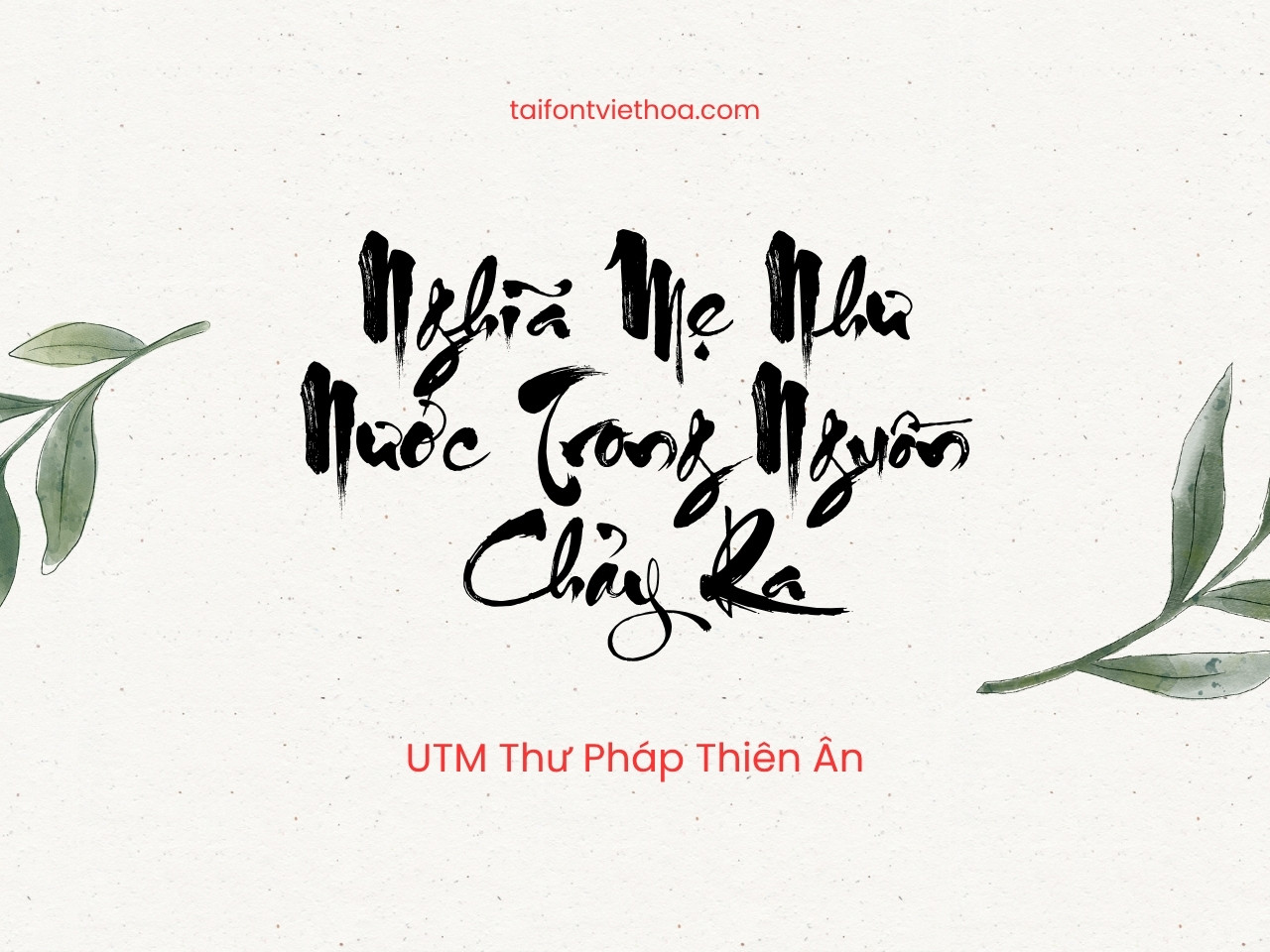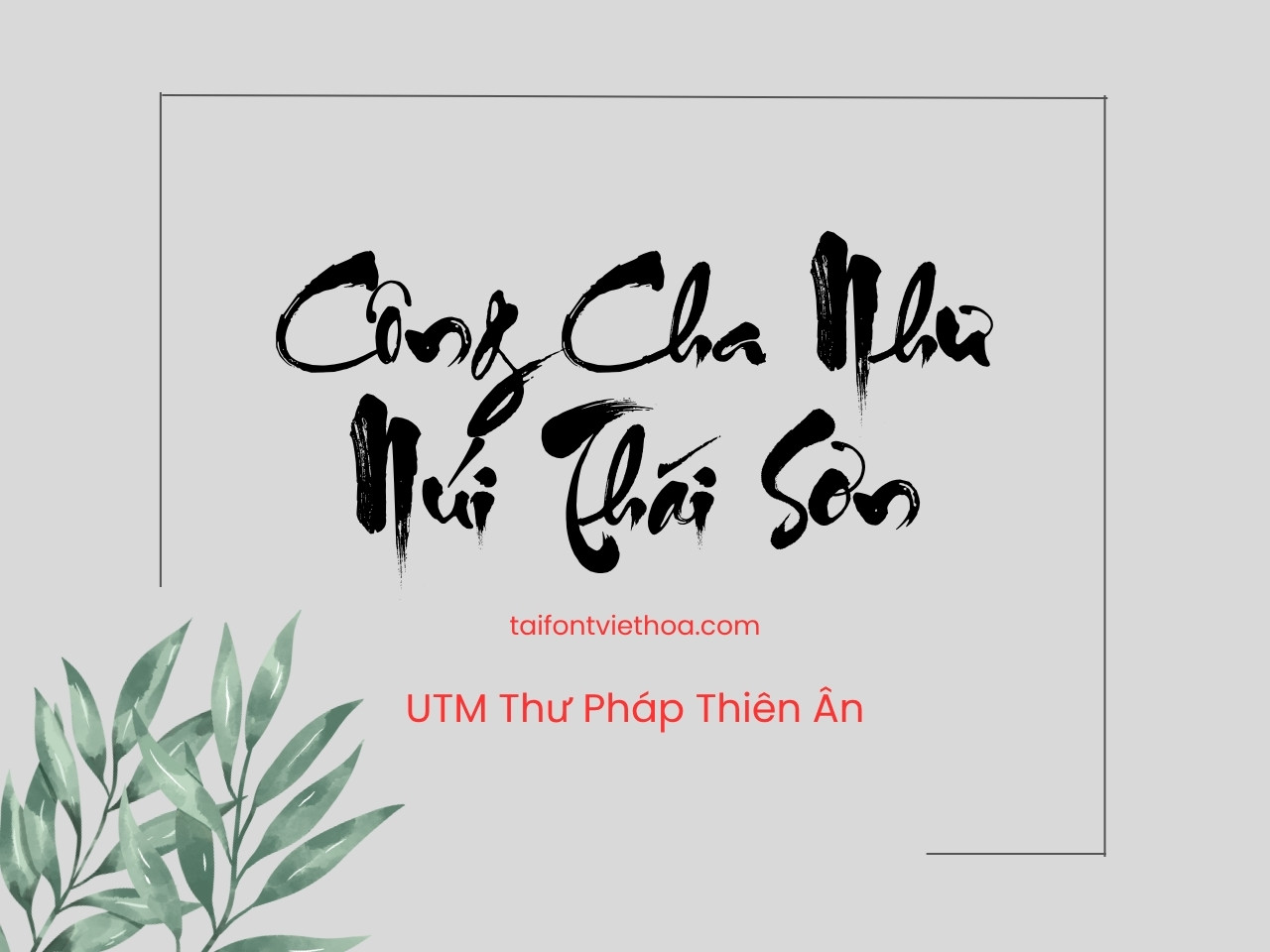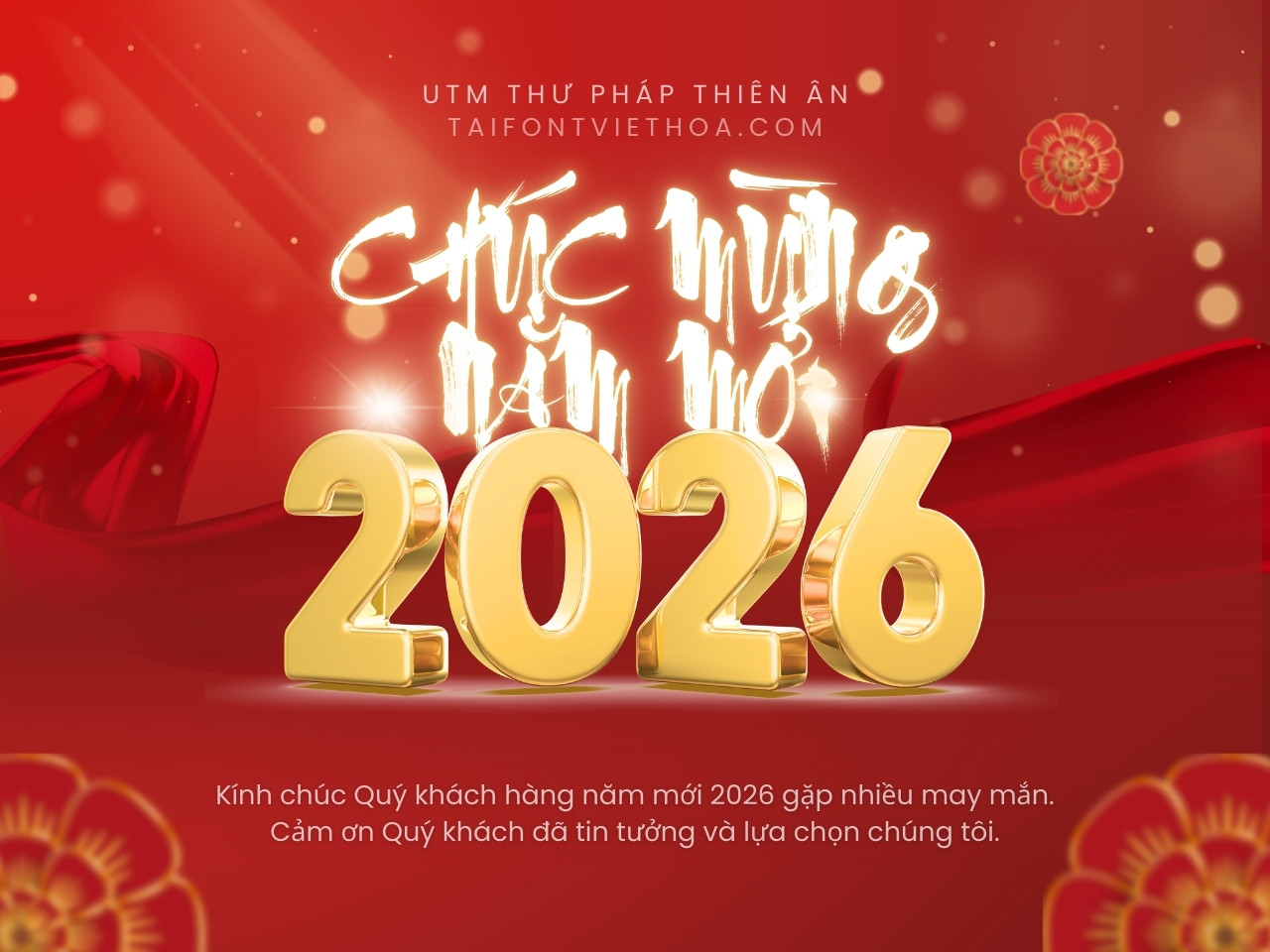
Font việt hóa UTM Thư Pháp Thiên Ân
Tác giả Font: Đinh Kiên
Giới thiệu về font UTM Thư Pháp Thiên Ân – Tinh hoa thư pháp Việt Nam
UTM Thư Pháp Thiên Ân là phiên bản Việt hóa của font Thư Pháp Thiên Ân – một kiểu chữ thư pháp mang đậm nét truyền thống và nghệ thuật Việt Nam. Font được thiết kế dựa trên phong cách viết tay thư pháp đặc trưng với các đường nét mềm mại, uyển chuyển và giàu cảm xúc, thể hiện vẻ đẹp tinh tế của văn hóa chữ viết Việt. Phiên bản Việt hóa đã được hoàn thiện để hỗ trợ đầy đủ tiếng Việt cùng nhiều ngôn ngữ khác, giúp mở rộng khả năng sử dụng trong các dự án mang tính văn hóa và nghệ thuật sâu sắc.
Font UTM Thư Pháp Thiên Ân được taifontviethoa.com sưu tầm và lựa chọn kỹ lưỡng nhằm phục vụ cộng đồng thiết kế Việt Nam. Phiên bản Việt hóa giữ nguyên nét mềm mại, bay bổng và đậm chất thư pháp truyền thống của bản gốc, đồng thời tối ưu khả năng hiển thị tiếng Việt, rất phù hợp cho các dự án thiệp cưới, thiết kế truyền thông văn hóa và cá nhân hóa mang phong cách thư pháp Việt Nam.
Đặc điểm thiết kế và ứng dụng của UTM Thư Pháp Thiên Ân
UTM Thư Pháp Thiên Ân sở hữu cấu trúc thư pháp với các nét bút thanh thoát, mềm mại và uyển chuyển, thể hiện sự tinh tế và nghệ thuật cao. Font có độ tương phản nhẹ nhàng, tạo cảm giác truyền thống và sâu lắng, rất thích hợp cho các thiết kế mang phong cách thư pháp Việt Nam và nghệ thuật dân gian. Font được trang bị các ligature và glyph đặc biệt giúp tăng tính linh hoạt trong thiết kế.
Font việt hóa UTM Thư Pháp Thiên Ân
Font thích hợp sử dụng trong các ứng dụng như thiệp cưới, thiệp mời, thiết kế poster nghệ thuật, bao bì sản phẩm thủ công và các dự án truyền thông mang tính văn hóa và cá nhân hóa cao. Ngành nghề phù hợp gồm: nghệ thuật, văn hóa, tổ chức sự kiện, thiết kế nội thất và quảng cáo truyền thống.